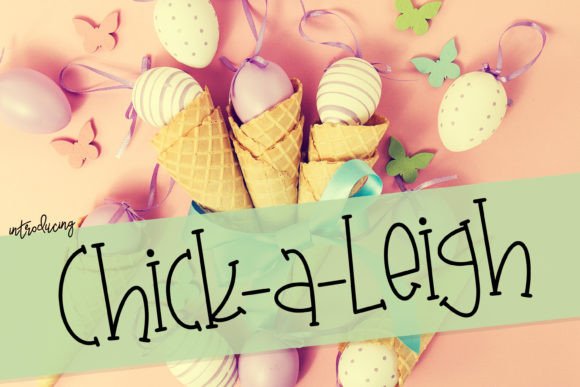
Chick-a-Leigh
Chick-a-Leighのような高品質の素材をお探しの場合、このプレミアムパッケージはクリエイティブなプロジェクトに素晴らしい選択です。
POD(オンデマンド印刷)製品、結婚式の招待状、またはソーシャルメディアのグラフィックを作成している場合でも、Chick-a-Leighは理想的です。